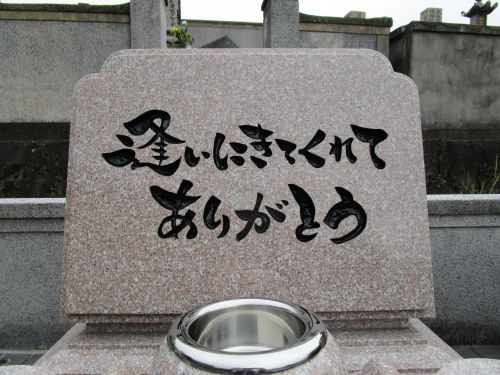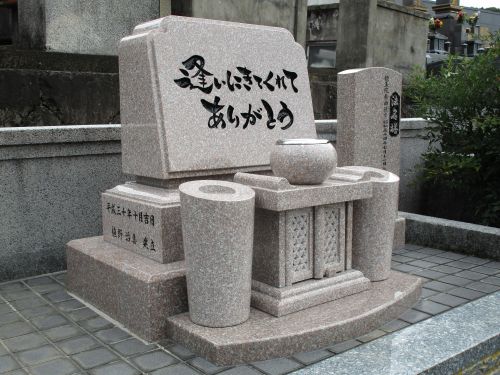
墓石に入れる文字 故人への思いを託す
今でも多いのは家名
墓石に何を彫るか、悩むところです。
やはり「山田家」など洋墓などでみる
ものは家名が半分くらいでしょうか。
書でお墓に入れる文字を書く場合、
イメージを膨らませてみます。
例えばどんな家庭だったのか?
楽しくワイワイといつも賑やかだった
物事を深く追求していくような家系
家族のことを一番に考えていたのか
まわりの人のために行動する人だったのか
色々と思いがよぎります。そんな思いを文字
に載せたい。
イメージを載せることができる。
つまり書にはご家族の気持ちを乗せることが
できます。
仕事一筋の父でした、力強い書で、
スポーツが好きなお父さんでした、躍動感が
ある書で。
いつも家をきれいにしていた母なら、整然と
した感じ。
おおらかなお母さんなら、のびのびとした
雰囲気を文字で表現。
心配性だったお母さんは、どうぞ安らかに
と安定した文字などはどうでしょうか。
お墓の種類やデザインも決まり、
彫る文字は何か我が家らしいものはないか
といった場合に書での家名を書き、実際に
墓石の図面に配置して、仕上がりを確認する
とこれでよかった!と思っていただけると幸
いです。
両家墓
少子化ということばが日常で聞かれるほどの
時代になりました。
お墓も後継が問題となっております。
実家の弟は結婚しておらず、後継がいないの
でお墓じまいをすすめられた、
など、家を継ぐことを重要としてきた社会の
構造が変わってきています。
地方出身のご夫婦のケース
九州と長野出身のご夫婦、
60代になって、なかなかお墓参りもできず
に、お彼岸やお盆の時期はいつも気になって
いたそうです。
それぞれを墓仕仕舞いをし
自宅近くの霊園に両家墓を建てることになり
ました。
一文字
和 絆 道 愛 慈
一文字のものも最近増えて参りました。
名前に因んだ一文字など自由に決めるケース
も多いようです。
新たに建てる場合、お墓のお引っ越しの際も
ご親戚との意見も伺いながら菩提寺がある場
合は相談してお決めになるのがよろしいかと
存じます。
言葉を入れる
「感謝」
「ありがとう」
「逢いに来てくれてありがとう」
お墓参りに来てくれる方へ、また生前への感
謝ともとれます。
お墓に入れる文字はみなさん悩まれるそうで
す。
施工例「逢いにきてくれてありがとう」
10月11日大安吉日に建立された
U様のお墓です。
はじめはどんな文字を入れようか悩んでいたところ、弊社のHPを見て
家族一同、これにしますとすぐ決まったそうです。
「お客様も林映寿先生の文字を大絶賛されて大変喜んでいました」。